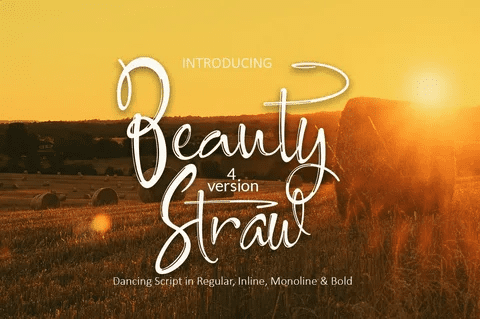
Название: Beauty Straw Font
Beauty Straw - это великолепный каллиграфический шрифт с высокой текстурой, идеально подходящий для использования в широком спектре современных дизайнов. Этот шрифт отлично смотрится в романтических приглашениях или сообщениях в социальных сетях, и превосходно подходит для заголовков Ваших работ.
Название: Beauty Straw Font
Beauty Straw - это великолепный каллиграфический шрифт с высокой текстурой, идеально подходящий для использования в широком спектре современных дизайнов. Этот шрифт отлично смотрится в романтических приглашениях или сообщениях в социальных сетях, и превосходно подходит для заголовков Ваших работ.